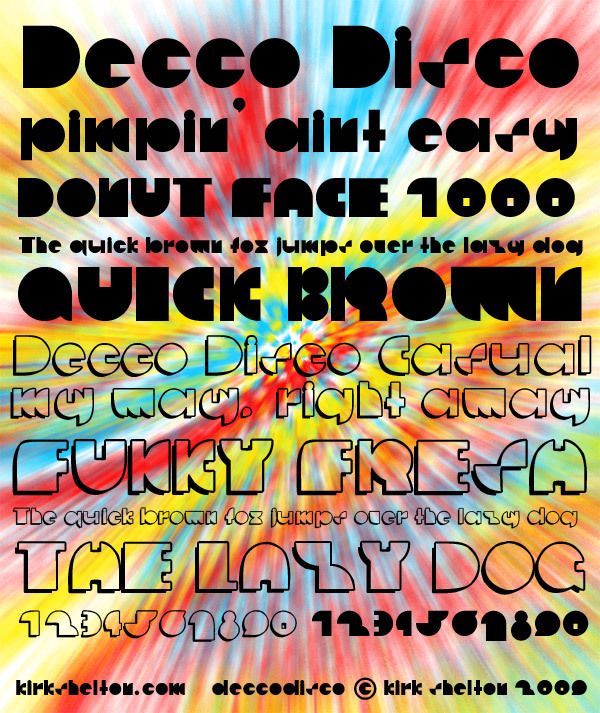
Deccodisco od Kirka Sheltona to darmowy, groovowy krój displayowy z pulsem ery disco i zabawnym, niemal geometrycznym charakterem. Litery zbudowane są z ciężkich, kolistych form, przełamanych wyraźnymi poziomymi nacięciami, co nadaje krojowi śmiały, rytmiczny wygląd, kojarzący się zarówno z wystrojem parkietów tanecznych, jak i grafiką telewizyjną w stylu retro.
Naturalnie sprawdza się na plakatach, ulotkach imprezowych, okładkach albumów, w brandingu wydarzeń i dużych projektach logo, zwłaszcza tam, gdzie krótkie słowo lub powtarzająca się nazwa mają przyciągać uwagę. Jako darmowy font, świetnie nadaje się również do nagłówków na okładkach, plansz tytułowych i wyrazistych tytułów, ponieważ zaokrąglone kształty i charakterystyczne wycięcia nadają nawet krótkim frazom silny rytm.